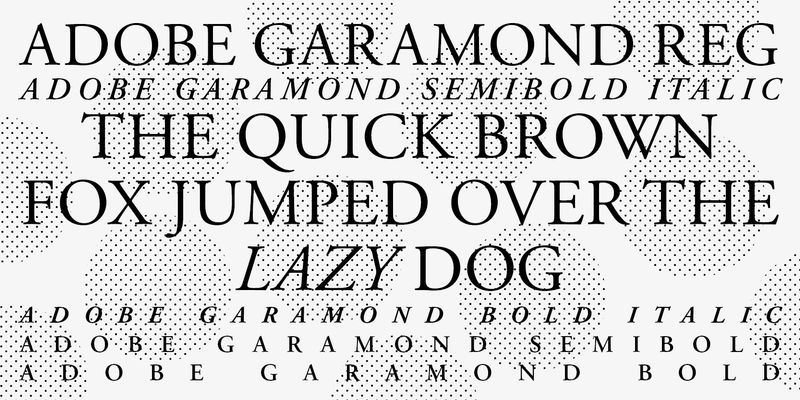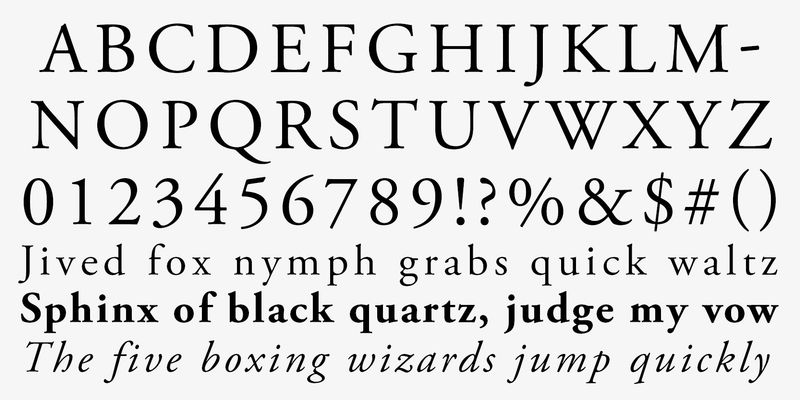
Adobe Garamond, ein Design von Adobe Originals und Adobes erstes historisches Revival, ist eine digitale Interpretation der lateinischen Schriften von Claude Garamond und der kursiven Schriften von Robert Granjon. Seit ihrer Veröffentlichung im Jahr 1989 hat sich die Adobe Garamond zu einem typografischen Grundnahrungsmittel in der Welt der Desktop-Typografie und des Designs entwickelt. Der Adobe-Schriftdesigner Robert Slimbach hat die Schönheit und Ausgewogenheit der ursprünglichen Garamond-Schriften eingefangen und gleichzeitig eine Schriftfamilie geschaffen, die alle Vorteile einer modernen digitalen Schriftfamilie bietet. Mit der Einführung der OpenType-Schriftentechnologie wurde Adobe Garamond als Pro-Schriftfamilie neu aufgelegt, die die Vorteile der fortschrittlichen typografischen Möglichkeiten von OpenType nutzt. Jetzt kann diese elegante Schriftfamilie mit noch größerer Effizienz und Präzision in OpenType-kompatiblen Anwendungen wie Adobe InDesign verwendet werden.
Das Adobe Originals-Programm wurde 1989 als hauseigene Foundry bei Adobe gegründet, um Originalschriften von beispielhafter Designqualität, technischer Treue und ästhetischer Langlebigkeit zu entwickeln.
Heute besteht die Aufgabe des Type-Teams darin, anspruchsvolle und sogar experimentelle Schriften zu entwickeln, die die Möglichkeiten von Design und Technologie ausloten. Die Schriftarten, die als Adobe Originals veröffentlicht werden, sind das Ergebnis jahrelanger Arbeit und Studien und gelten als Industriestandard für den Ehrgeiz und die Qualität ihrer Entwicklung.